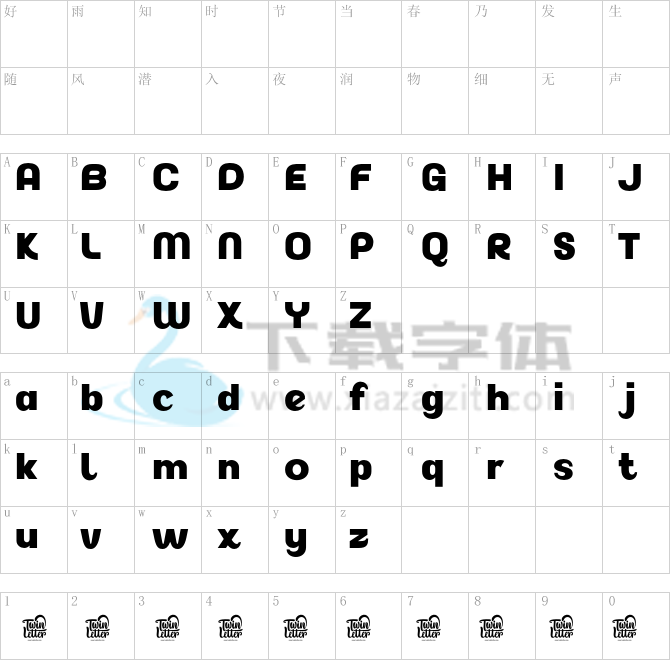
Akuina Black.otf字体下载,这款字体结构工整、笔画清晰,兼顾美观与易读性,适用于标题、正文、海报、包装、LOGO 等多种场景。字形优雅稳定,风格百搭耐看,适配日常排版与创意设计,让文字呈现更舒适、更具质感。Akuina Black.otf字体下载一笔一画,皆是细节,以均衡的比例、流畅的线条打造舒适视觉体验,字形端正大气,风格简约现代。无论是商业设计、品牌宣传还是日常排版,都能轻松驾驭,让文字更有格调与力量。Akuina Black.otf字体下载字体下载。